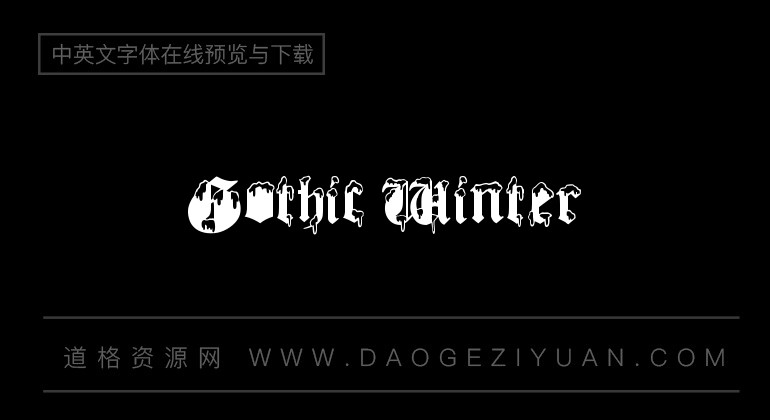
Gothic Winter是一种装饰性的手写风格字体,适用于设计手稿、海报、贺卡、书籍封面等各种项目。与其他手写风格字体不同,Gothic Winter的字母形状略带诡异和神秘,但依然保留了一些现代和流畅的元素。 其设计灵感来源于中世纪时期的书法风格,同时还融合了一些当代艺术的特点。字母的线条流畅,有时略带雕刻感,使得文字具有非常独特的视觉效果。 Gothic Winter字体有多种风格,包括粗体、斜体和正常字体,可供设计师灵活使用,以满足不同设计需求。如果你正在寻找一种充满冬季气息、富有神秘感和独特视觉效果的字体,那么Gothic Winter可能是一个不错的选择。内容介绍
Gothic Winter是一款非常不错的手写艺术字体,具有很好的视觉感,适合于文化类的宣传设计、商业类品牌的广告和产品包装设计以及个性化文字排版等较多场景。